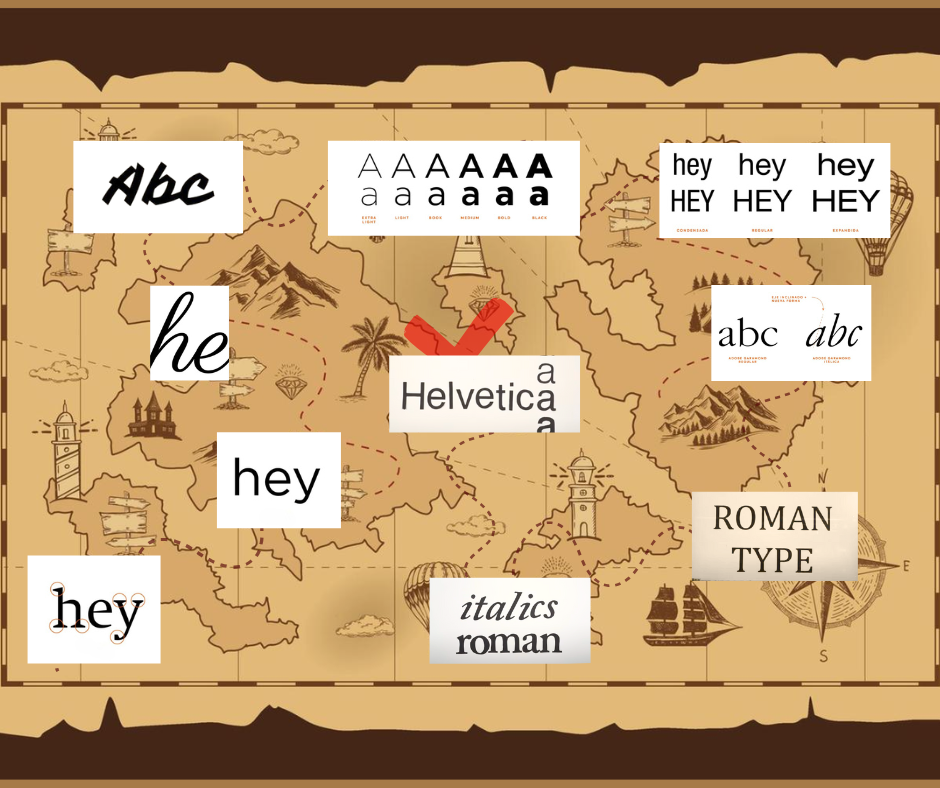
mapa de tipografías
aprende las tipografía
1 tipografía inspirado en las inscripciones romana 2 fue creada por Nicolas Jenson 3 Es un estilo tipográfico universal 4 tipografía sin serifa 5 tipogrfia con serifa 6 tipografía manuscrita 7 tipografía decorativa 8 variable tipográfica de peso 9 variable tipográfica por separación 10 variable tipográfica por inclinación